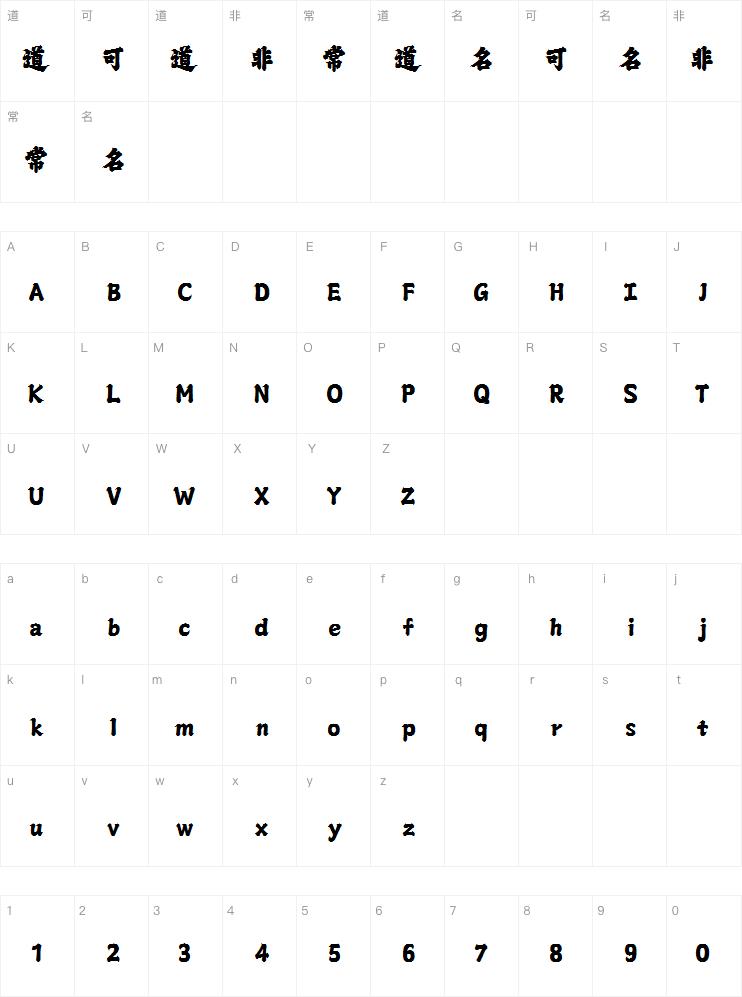
山海龙虎榜书,是一款全新的字体,包含简繁汉字9169个,符号200+个,是一款大字榜书字体。该字体雄健有力,非常醒目!有力、宽厚,如同巍峨的大山,充满了稳重感和设计感。古朴浑厚,笔画与字形间透露着榜书的古雅和刚劲的特点,在浑厚的同时而又极富张力,桀骜不驯的特性,霸气外露。它的笔画充满力量感,组合搭配极富强烈的节奏感。在粗细的纵横间,拥有非常规的张力特性。从而使得该字体字形在浑厚的同时而又极富张力。它的笔画充满力量感的同时,又蕴含着朴拙感。在粗细的纵横间,拥有非常规的张力特性。笔画的楷书运笔笔势效果使字体的气息更加流畅,笔画间的关系密不可分,同时也增加了字体的自由洒脱之感。这款字体古韵悠扬而不失灵动,静中有动,收放有序,适合作为标题字体应用于书籍封面、影视标题、展览广告等多种场景。